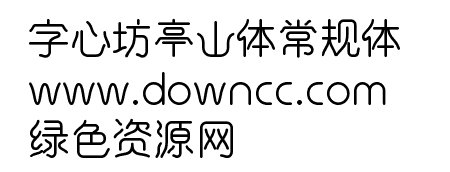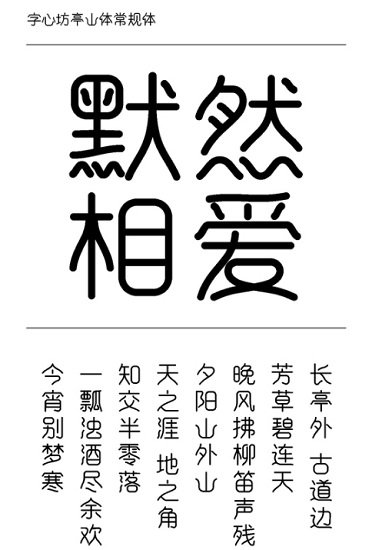
字心坊亭山體是一款很有象形字特色的藝術(shù)字體,打破筆畫(huà)端正筆直的常規(guī)感,讓其如流水般更具有動(dòng)態(tài)美,結(jié)構(gòu)大方,看起來(lái)十分舒適優(yōu)雅,綠色資源網(wǎng)今日推薦!
神似篆字體,形似傳統(tǒng)黑,又有藝術(shù)設(shè)計(jì)在里面,耳目一新,與現(xiàn)有的字體產(chǎn)品大相徑庭。此款筆畫(huà)采用柔線柔邊設(shè)計(jì),風(fēng)行水上,自然流暢。特別適用于影視、動(dòng)畫(huà)、游戲、海報(bào)、書(shū)籍、LOGO等方面。
該字體為字心坊亭山體字體系列作品的常規(guī)款字型字體。
創(chuàng)作靈感來(lái)源于山水亭舟的水墨風(fēng)景畫(huà),汲取古代篆體的部分筆畫(huà)風(fēng)格特征,輔以黑體字體結(jié)構(gòu)的方正、簡(jiǎn)潔、粗細(xì)均勻,在此基礎(chǔ)上對(duì)部分筆畫(huà)、偏旁、結(jié)構(gòu)進(jìn)行藝術(shù)再加工。